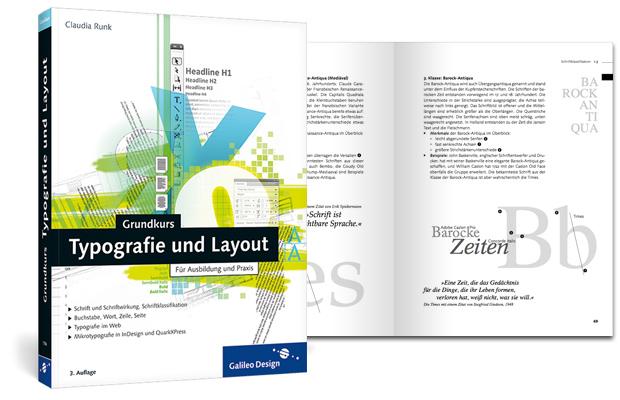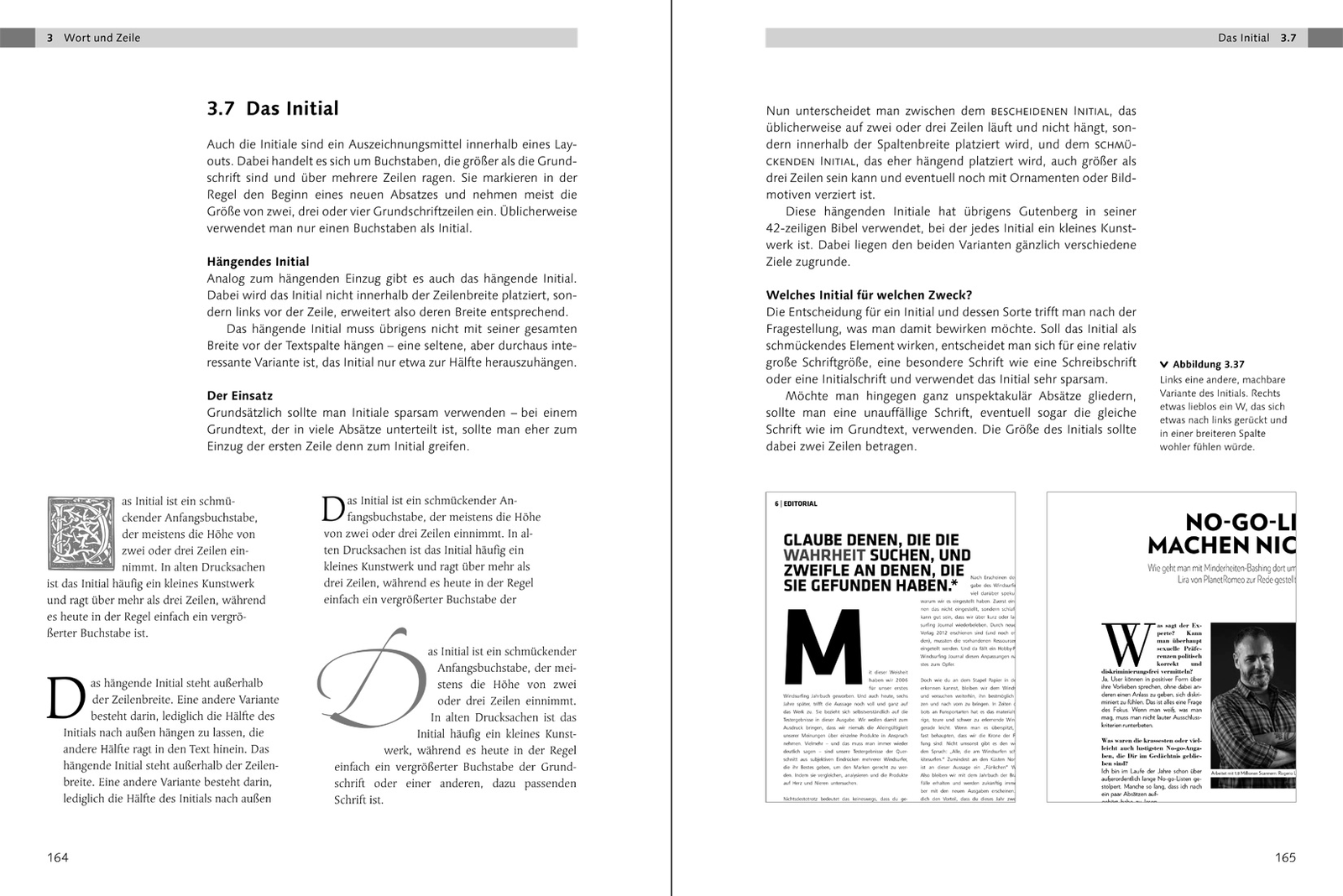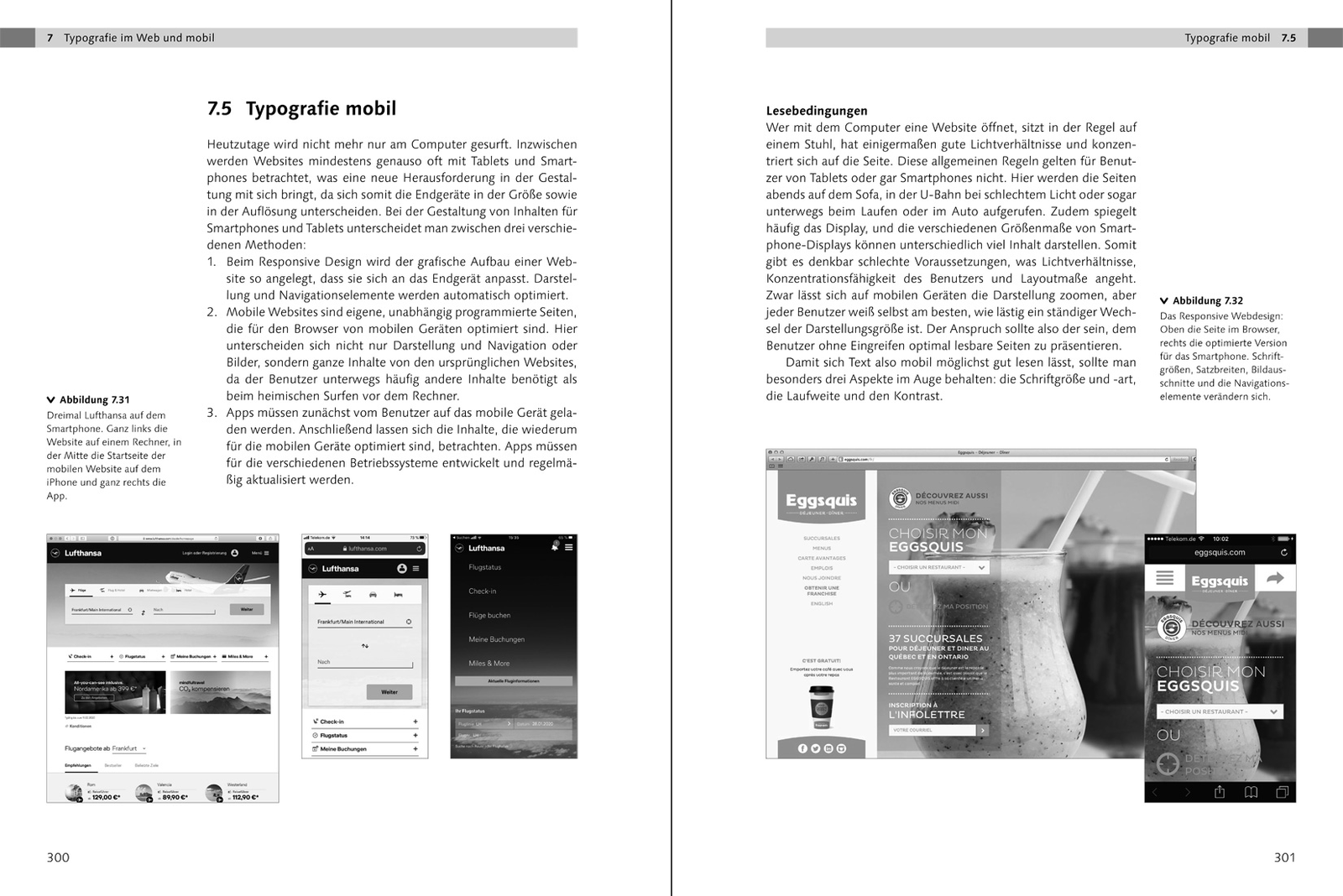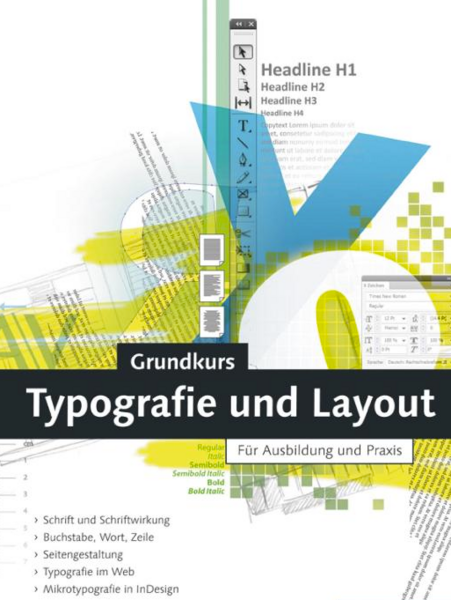
Brille: Fielmann. Typo-Buch: Hermann Schmidt. Na gut, Niggli,und Stiebner gibt es auch noch, aber wenn sich andere Verlage an entsprechenden Büchern im deutschsprachigen Raum versuchen, gelingt nur selten eine breite Bekanntheit im Fachbereich des Grafikdesigns. So war mir auch persönlich das Buch »Grundkurs Typografie und Grafikdesign« des Rheinwerk-Verlags bislang nicht aufgefallen, das gerade in der dritten, aktualisierten Auflage erschienen ist. Dabei hat das Buch doch einiges zu bieten …
Die Autorin Claudia Korthaus ist gelernte Schriftsetzerin und heute unter anderem als Redakteurin (MACup/Macwelt) und Dozentin (HDPK Berlin) tätig. Ihr Buch wagt den Rundumschlag, auf 319 Seiten die komplette typografische Anwendung zu behandeln. Dies beginnt wie üblich mit einer Einführung in die Schriftgeschichte und die typografischen Grundbegriffe vom Bleisatz bis zum Desktop Publishing. Daneben werden ausgewählte Schriftkünstler behandelt und natürlich Schriftklassifikationssysteme vorgestellt. Die folgenden Kapitel widmen sich dann ausführlich den typografischen Grundlagen und ihrer Anwendung im heutigen Satz. Die Kapital sind dabei stufenweise (Das Zeichen; Wort und Zeile; die Seite; die Gesamtkomposition) aufgebaut. Darüber hinaus gibt es ein Kapitel zu Schrift im Web und zu Schrifttechnologien (Fontformate, Unicode etc.). Das komplette Inhaltsverzeichnis kann hier eingesehen werden.
Das Buch erscheint als einfaches Paperback, vollständig in schwarz-weiß und im üblichen Galileo-Layout in Syntax gesetzt. So lässt sich der für Einsteiger sicher passende Preis von 24,90 Euro erreichen. Mit opulenten Hochglanzbildern kann und will das Buch also nicht dienen.
Der Inhalt ist Trumpf – und der kann doch sehr überzeugen. Passend zum sonstigen Verlagsprogramm bei Galileo Press ist das vermittelte Wissen stets sehr praxisbasiert und auf den Computereinsatz zugeschnitten – etwa wenn es darum geht, wie bestimmte Einstellungen konkret in InDesign und QuarkXPress vorzunehmen sind.
Und man merkt hier der Autorin auch an, dass sie Ihr Element beherrscht und es auch regelmäßig anderen vermittelt. Viele Fachbücher beziehen sich in ihren Inhalten auf zuvor erschiene Fachbücher und so werden nicht selten unreflektiert veraltete Lehrmeinungen übernommen. Frau Runk zeigt hier viel liebe für’s Detail bei der Recherche und selbst bei strittigen Fragen wie etwa dem Ursprung der Serifen, wird nicht vorschnell zu veralteten oder vereinfachten Meinungen gegriffen, sondern auf verschiedenen Thesen hingewiesen.
Ebenfalls löblich ist die Aktualität des Buches. Während sich viele Einsteiger-Bücher eher auf die immer wieder gleichen, klassischen Typografie-Inhalte beschränken, widmet sich »Grundkurs Typografie und Layout« sogar ausführlich den allerneuesten Entwicklungen rund die Einbindung von Schriften im Internet.
Empfohlen werden kann das Buch somit allen Einsteigern in die typografische Gestaltung. Der Umfang, Aufbau und der einfache Schreibstil des Buches macht es dabei nicht nur für Grafikdesign-Studenten interessant, sondern tatsächlich auch insbesondere für alle Laien und Quereinsteiger, die sich mit den Regeln guten Designs im Allgemeinen, und deren konkrete Anwendung in professionellen Layoutprogrammen wie Adobe InDesign oder QuarkXPress auseinandersetzen wollen.
Untertitel: Für Ausbildung und Praxis
Autor(en): Claudia Korthaus (Runk)